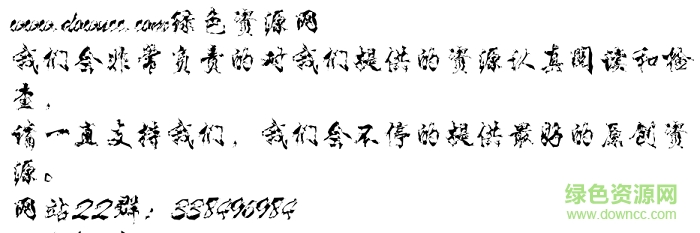
福順穿花浪影字體是一款造型明明滅滅、隱隱約約的藝術(shù)字體,給人看不清晰、琢磨不透的秘密感,喜歡本作品的朋友歡迎來綠色資源網(wǎng)下載體驗哦!
穿花浪影采用了海浪的特色形態(tài)為模板,給人若隱若現(xiàn)的獨特視覺呈現(xiàn),字體閃爍如浪影、生動活潑似廢話,藝術(shù)內(nèi)涵十分豐富,可適用于藝術(shù)設(shè)計、海報設(shè)計等創(chuàng)意設(shè)計場合!
浪影,釋義:形容蹤跡漂泊不定,就象流水和浮萍一樣。 出處 明·湯顯祖《牡丹亭》第二十出:“恨怱怱,萍蹤浪影,風(fēng)剪了玉芙蓉。”